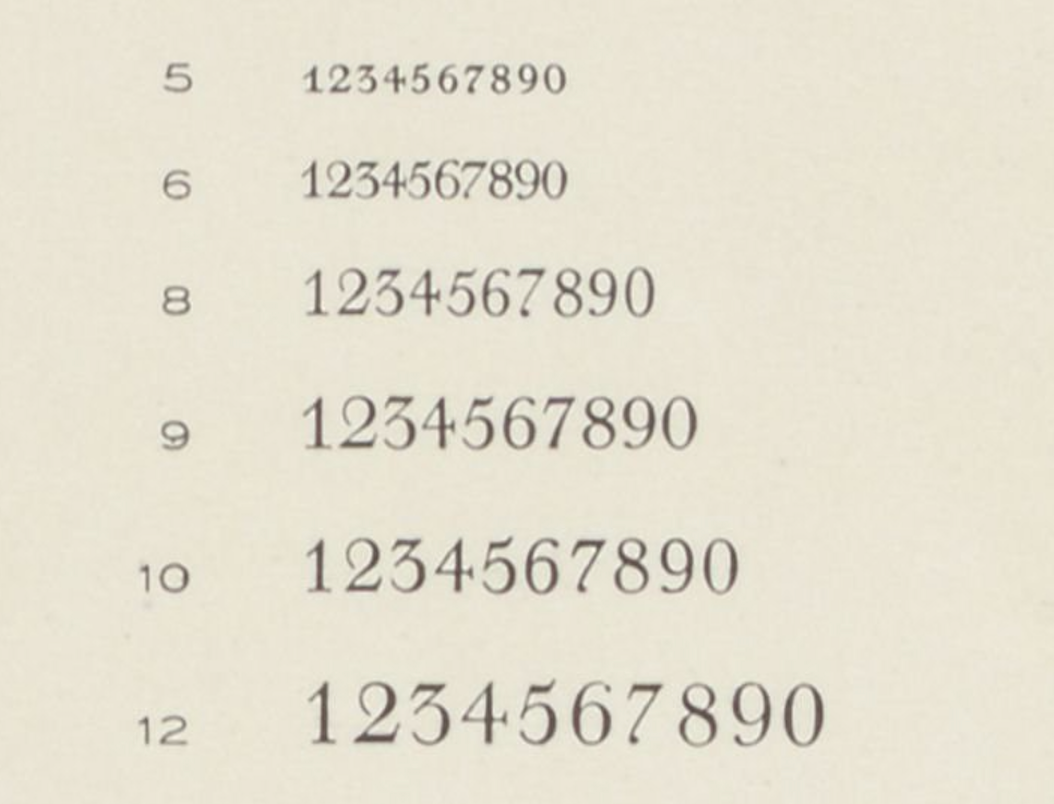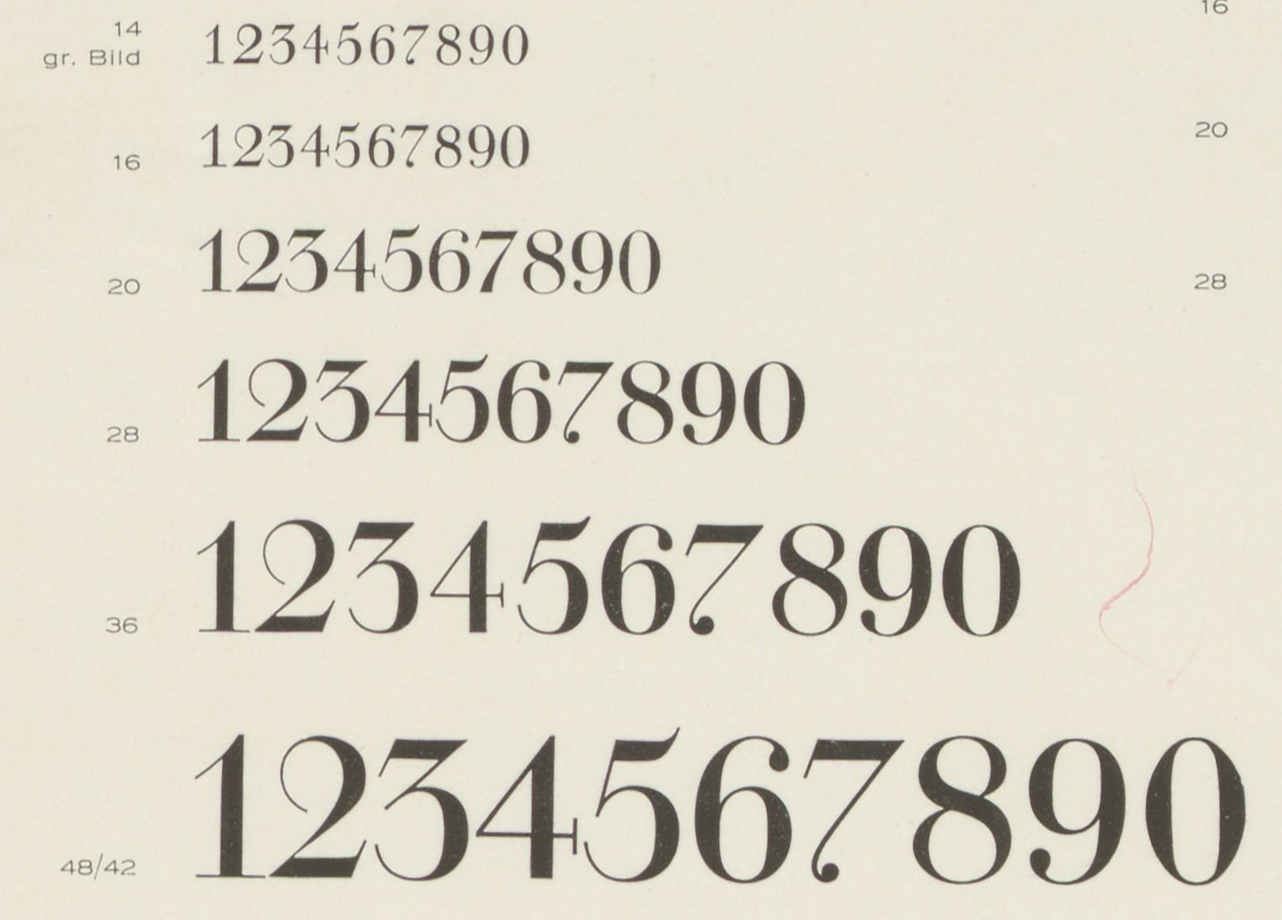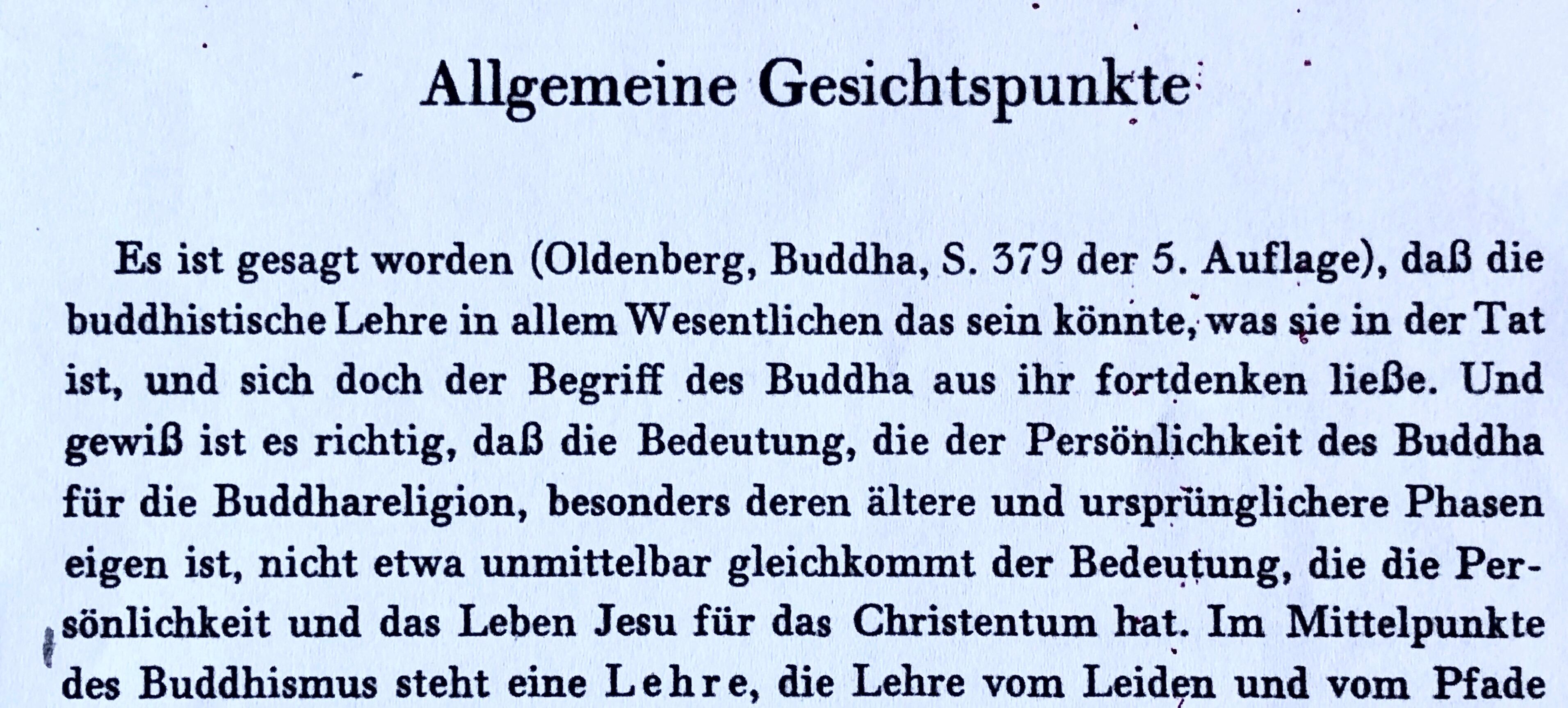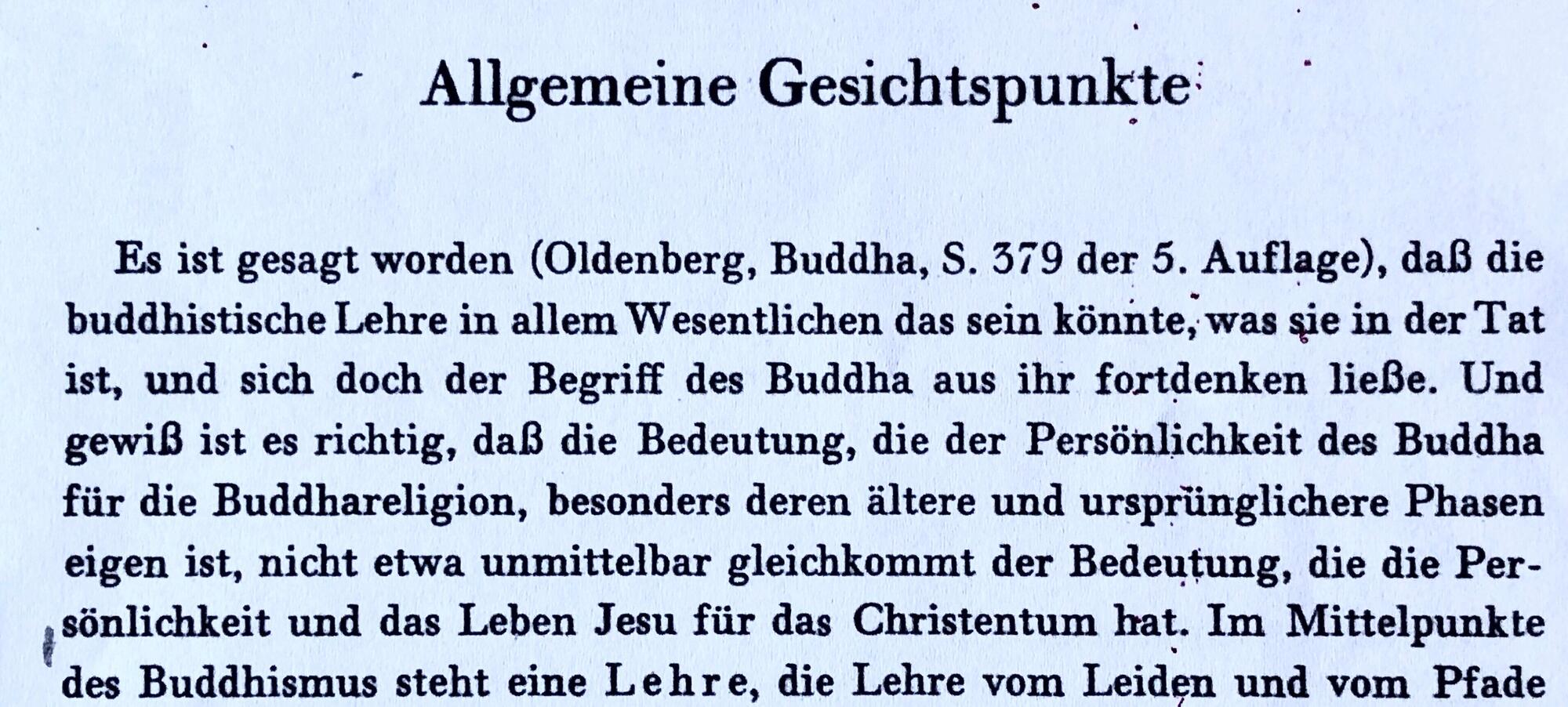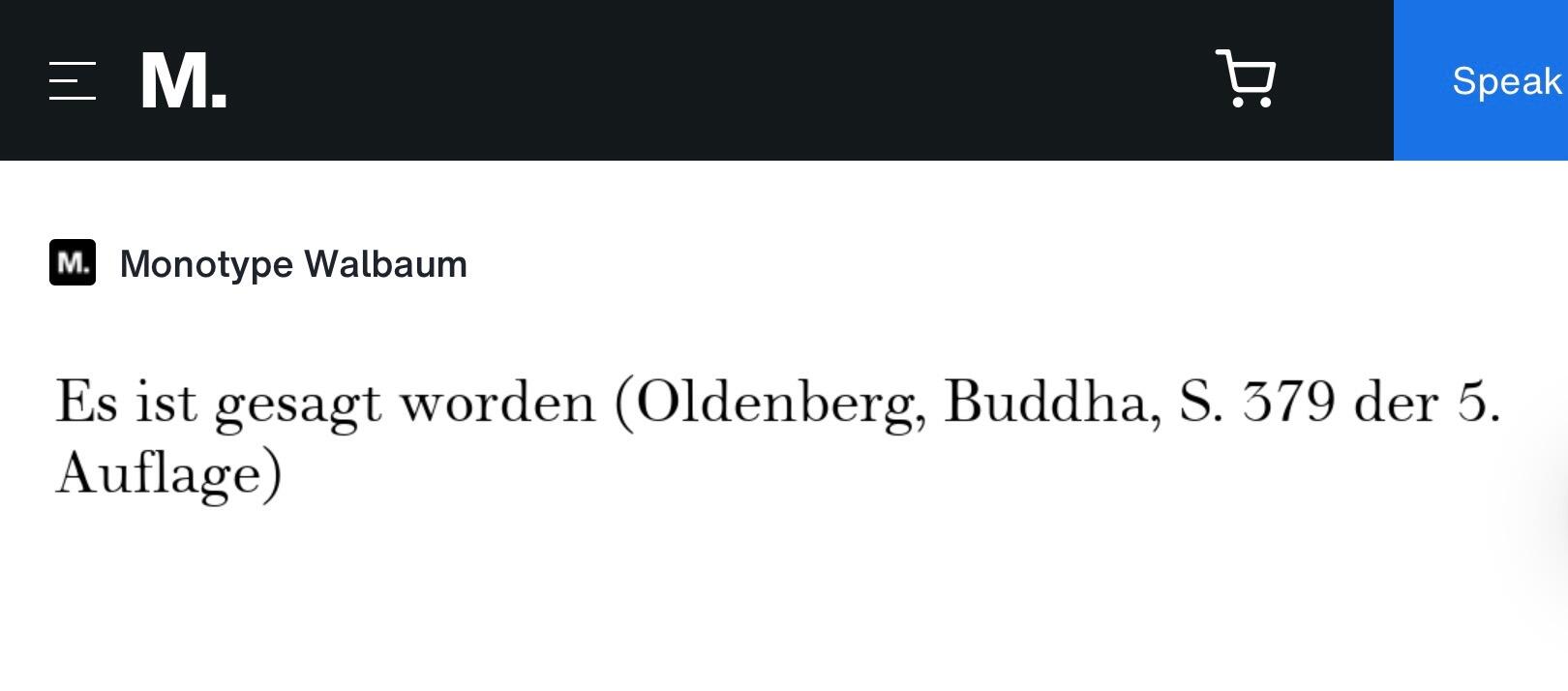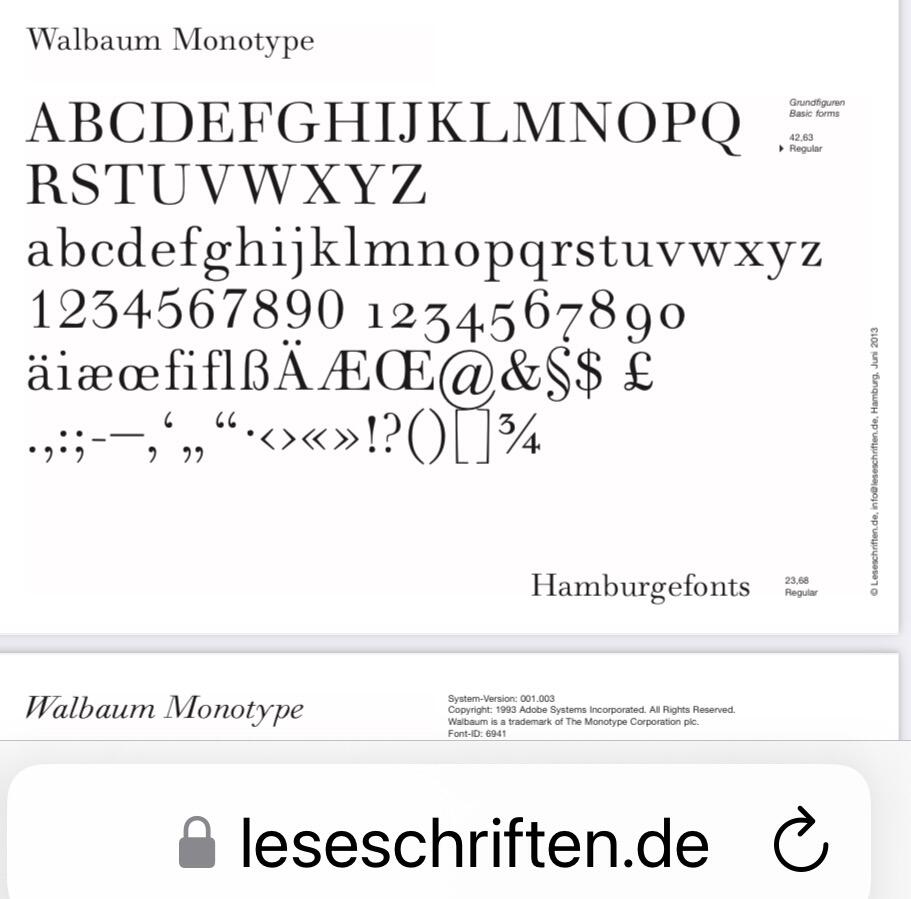
50-iger Jahre Buchschrift? Suche diesen oder ähnlichen Fonts (Buddha und seine Lehre)
Buch:
Buddha und seine Lehre
Verlag Freies Geistesleben
1958
ISBN: 3-8251-7222-8
Ich habe ein paar Schriftproben gemacht. Der Hauptunterschied ist wohl bei den Ziffern.
Die Derivate Cenntennial von Adrian Frutiger und Kepler von Robert Slimbach sind zumindest bei den Ziffern ähnlich meiner Vorlage. Aber die sind ja nach 1958 erschienen.
Interessant!
Ich habe die Schrift dank deiner Hilfe gefunden.
Es ist die Walbaum von Monotype:
Jetzt hat sich noch ein weitere Frage ergeben. Gibt es eine Schrift, die für Pali-, Sanskritworte geeignet ist (Buch »Buddha und seine Lehre« erschien 1958)?